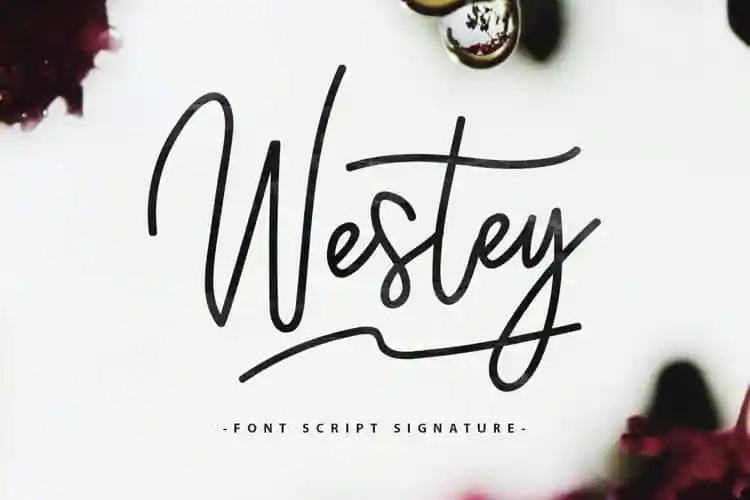
Westey Handwritten Font
Westey Handwritten Font é uma fonte de letra escrita à mão que traz uma mistura encantadora de suavidade e brilho. Suave e divertida, mas também um toque criativo. Esta fonte moderna e elegante é perfeita para design de cartões de casamento, logotipos, cabeçalhos de sites e até mesmo desenhos de moda. Westey oferece 73 alternativas de símbolos e 63 caracteres escritos à mão que adicionam uma dimensão única ao seu projeto. Inclui um conjunto completo de letras maiúsculas e minúsculas, tanto em português quanto em outros idiomas, juntamente com uma ampla gama de sinais de pontuação e números. Esta fonte é a escolha perfeita para aqueles que querem dar vida aos seus projetos com um toque sofisticado e autêntico. Com Westey, você pode adicionar um charme único e pessoal à sua identidade visual ou ao seu design gráfico de qualquer tipo – seja ele cartões de festa, logotipos criativos ou até mesmo designs de moda inovadores. Não espere mais e download a fonte Westey Handwritten Font para começar a transformar seus projetos em verdadeiros hit!